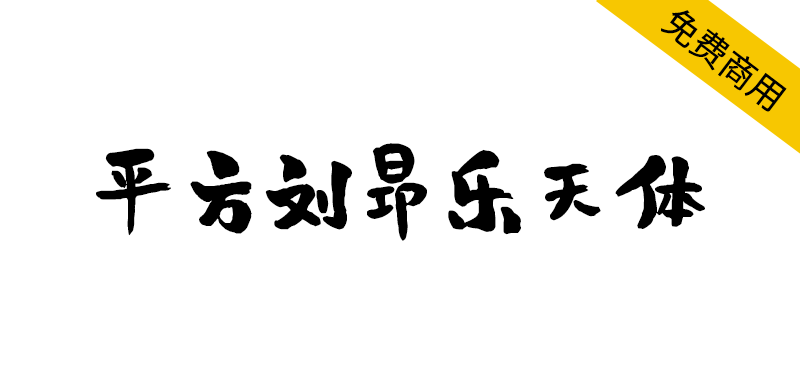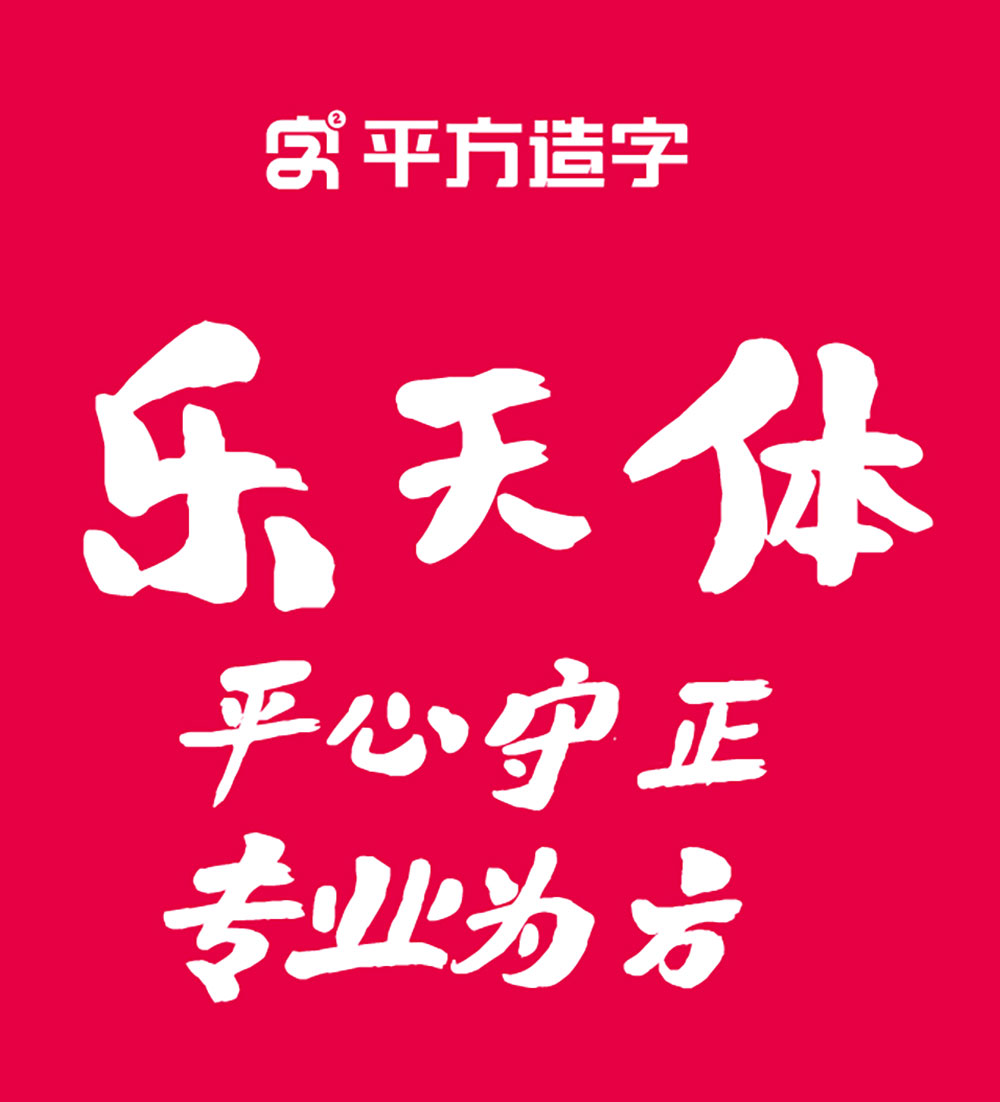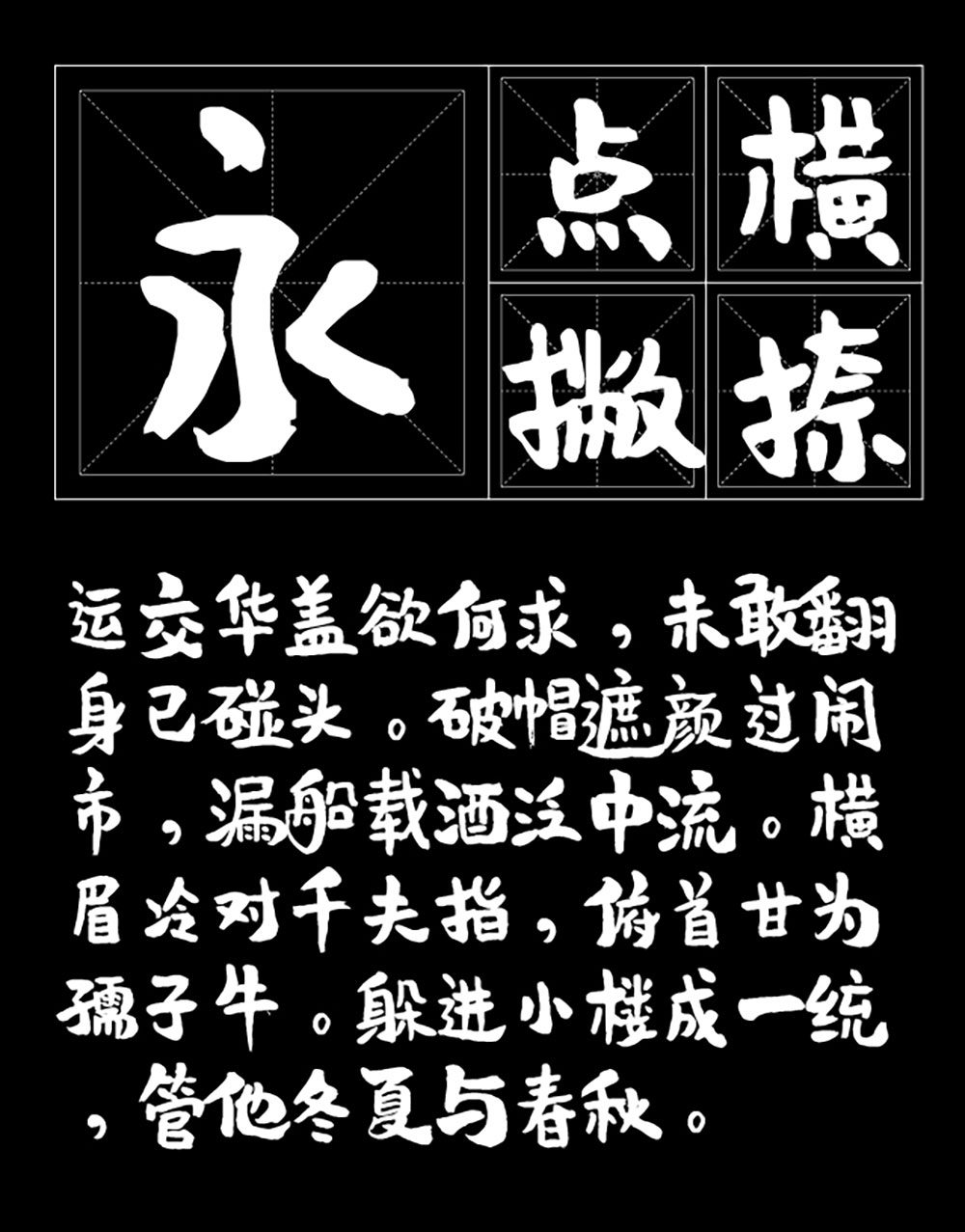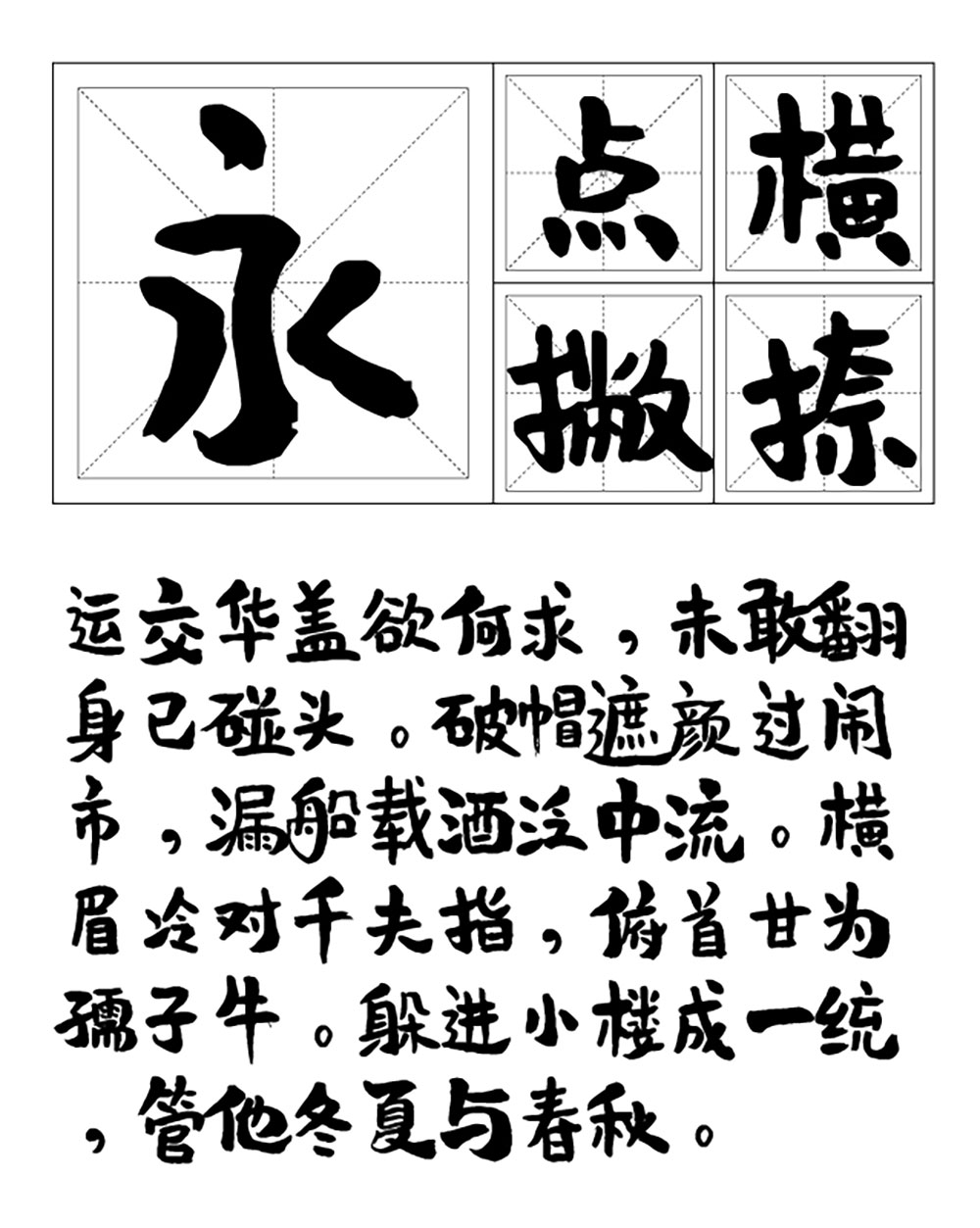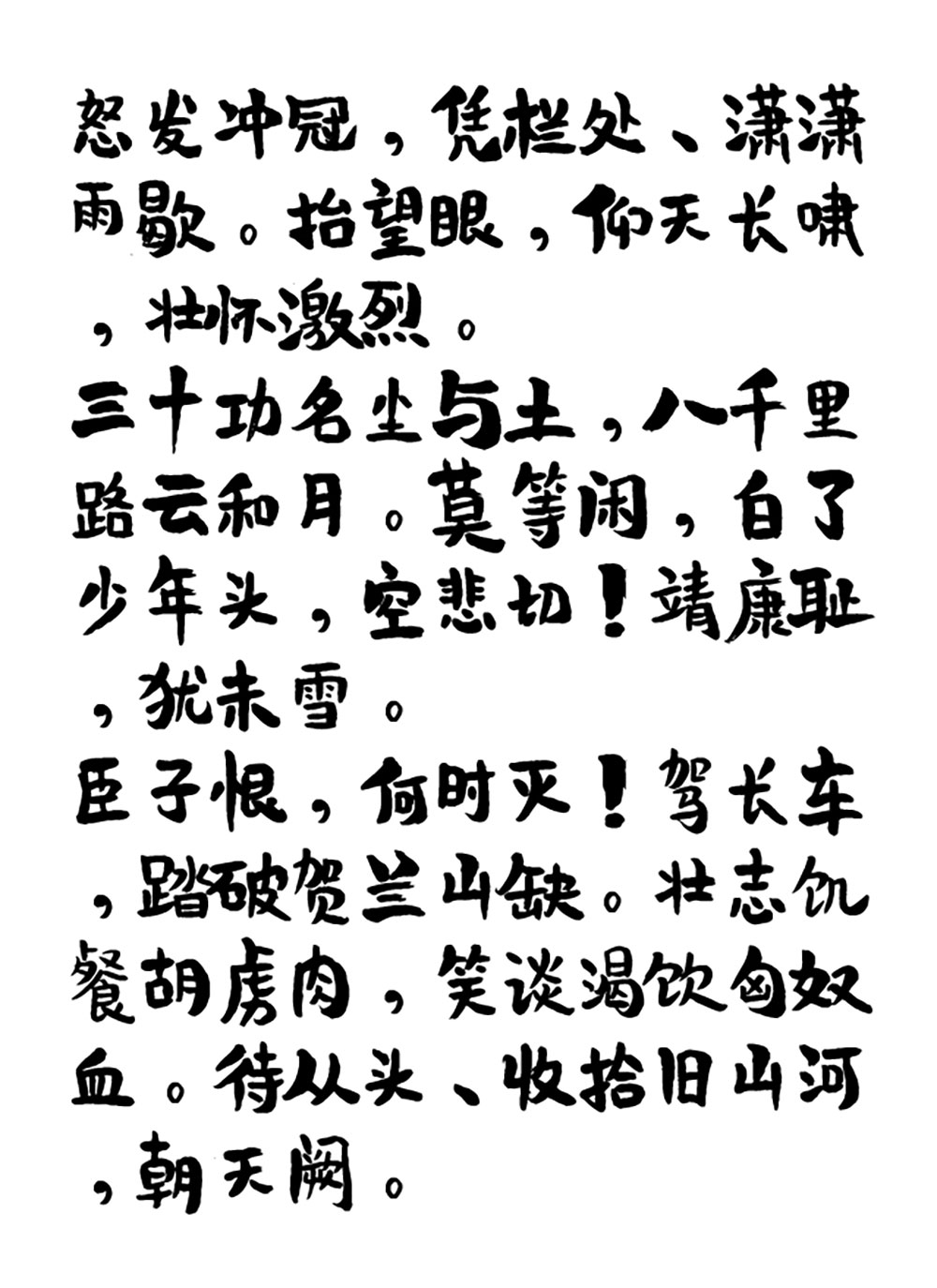
【平方刘昂乐天体】一款风趣活泼的创意手写体字体
还在为设计作品缺乏个性而烦恼?这款由设计师刘昂所创作的毛笔手写体将颠覆你的认知!平方刘昂乐天体以生动的笔触再现传统书法韵律,墨色浓淡相宜,完美融合艺术感与现代设计。最令人惊喜的是,这款包含6763个汉字的专业字体竟完全免费商用!从广告海报到电商设计,让你的作品瞬间脱颖而出。想知道如何用这款字体为设计注入灵魂?
【平方刘昂乐天体】一款风趣活泼的创意手写体字体
平方刘昂乐天体是一款独具特色的毛笔手写风格字体,其笔触生动展现了毛笔书写的自然韵律。字体笔画粗细变化丰富,起笔处力道浑厚,墨色浓淡相宜,完美呈现传统毛笔的墨韵效果。这款字体适合应用于印刷包装设计、广告海报创作、影视游戏界面等各类需要艺术化文字排版的领域。
平方刘昂乐天体由字体设计师刘昂所所创作,字体特点风趣活泼适用于各种场合,内容中文简体字库。字体采用OpenType格式,基于中华人民共和国GB2312-80字符集标准,共收容字数6763汉字,常用标点符号123个,共计字符6886个。